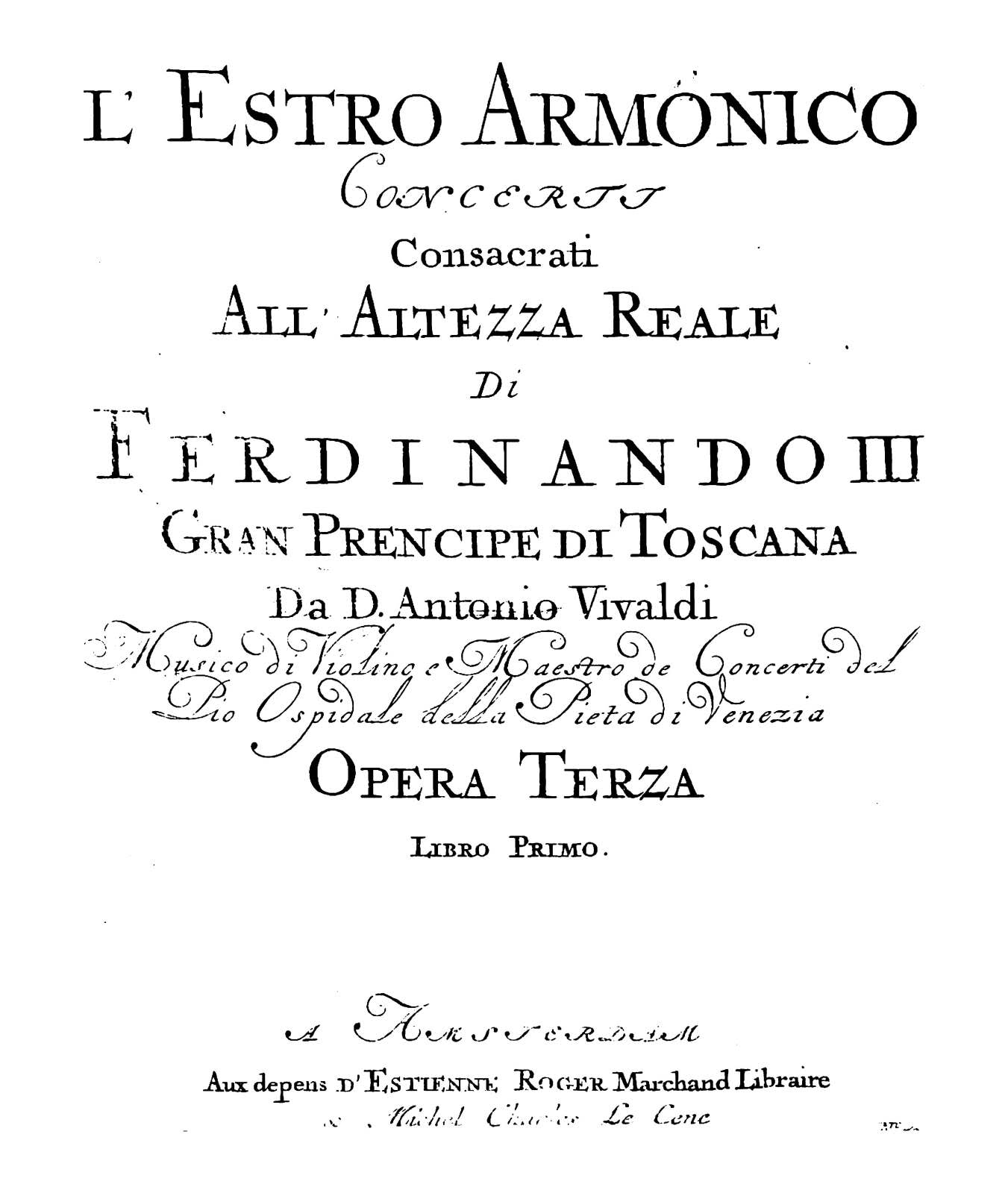
Noten-Titelblatt
Hat jemand eine Idee, welche digitale Schrift derjenigen auf dem Titelblatt nahekommt (oder typografisch "Amsterdam um 1720" austrahlt)? Es geht vor allem um die Serifenschrift, Hinweise auf die Schreibschrift sind aber auch willkommen ...
(Es ist übrigens Vivaldis op. 3 bei Estienne Roger - die entscheidenden Infos sind im Bild abgeschnitten ...)
Falsches Jahrhundert, falscher Ort, aber trotzdem könnte sie dir dafür gefallen: Tierra Nueva, gestaltet von Sebastian Nagel, verkauft von Ralf Herrmann => bleibt alles im Forum. ;)
Ich würde trotzdem eher etwas in Richtung MVB Sirenne vorschlagen:
Zur Schreibschrift: vielleicht etwas von P22
(trifft's aber nicht ganz - da gibt es sicher bessere Entsprechungen wenn es eine 1:1-Umsetzung sein soll)
Cochin Archaic passt ziemlich gut, finde ich. Z.B. das R, G und der allgemein unregelmäßige Vintage-Charakter.
Oder auch die Nicolas Cochin.
Genau das vom Notenheft (bzw. auch nur annähernd unbereinigt) wirst Du sicher in der digitalen Welt nicht finden, aber die Cochin kommt dem schon recht nahe.
Ach ja, Lilypond ... Ich frage mich, warum dieses Programm noch immer einen so guten Ruf hat. Einige der auf der Internetseite beschriebenen Probleme (schlechte Ergebnisse anderer Notensatzprogramme mit jeweiligen default-Einstellungen) haben vielleicht vor einigen Jahren noch bestanden, treffen aber mittlerweile nach meiner Erfahrung nicht mehr zu (man beachte etwa das sehr schöne "magnetische Layout" von Sibelius 6, das automatisch Kollisionen vermeidet). Dagegen habe ich sehr viele mit Lilypond gesetzte Noten gesehen, die wirklich sehr hässlich aussahen (zum Stöbern: http://www.mutopiaproject.org/).
Ich glaube, Score wird von einigen Notensetzern bevorzugt, weil es gar nichts automatisch macht. Man kann also seine Noten auf dem Bildschirm, resp. Notenblatt verteilen, wie man es in klassischen Notensatzzeiten gemacht hätte. Ob das Ergebnis dann besser aussieht als in Programmen wie Sibelius oder Finale hängt vermutlich eher mit den Fähigkeiten des Setzers als mit denen des Programms zusammen. Ich würde aber gern wissen, wie einige Detaileinstellungen in Score gehandhabt werden. In Sibelius gibt es z.B. keine Möglichkeit, kleinere Notenzeilen anders als durch Skalierung zu erzeugen - mit dem Ergebnis, dass sie nicht nur kleiner, sondern auch dünner sind ... aber das führt jetzt vielleicht zu weit ...
Schönen Sonntage!